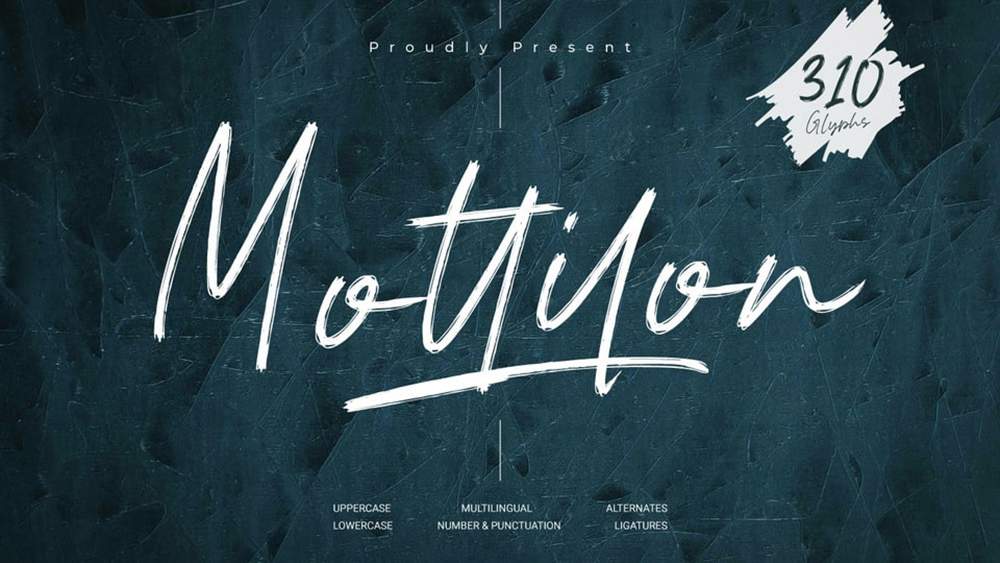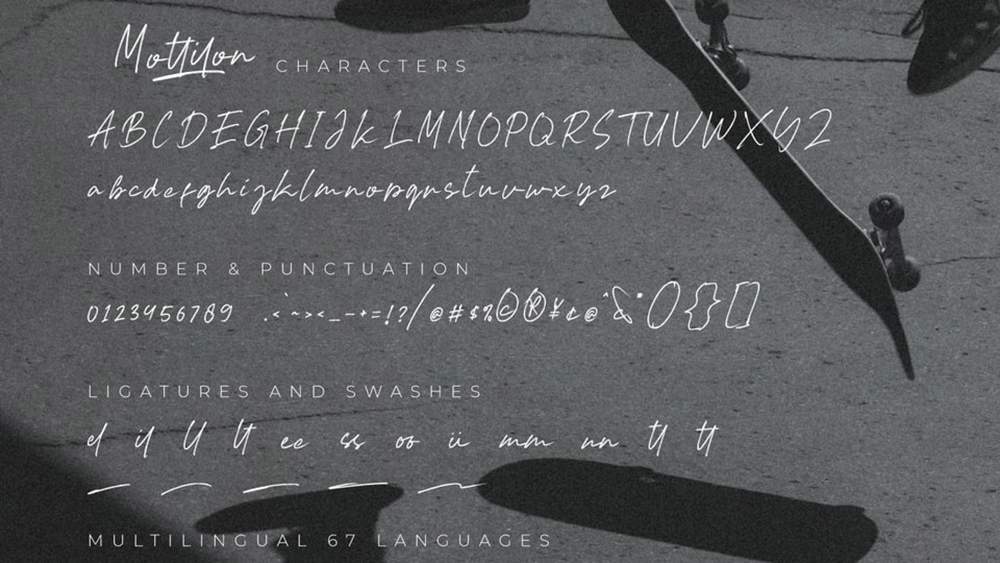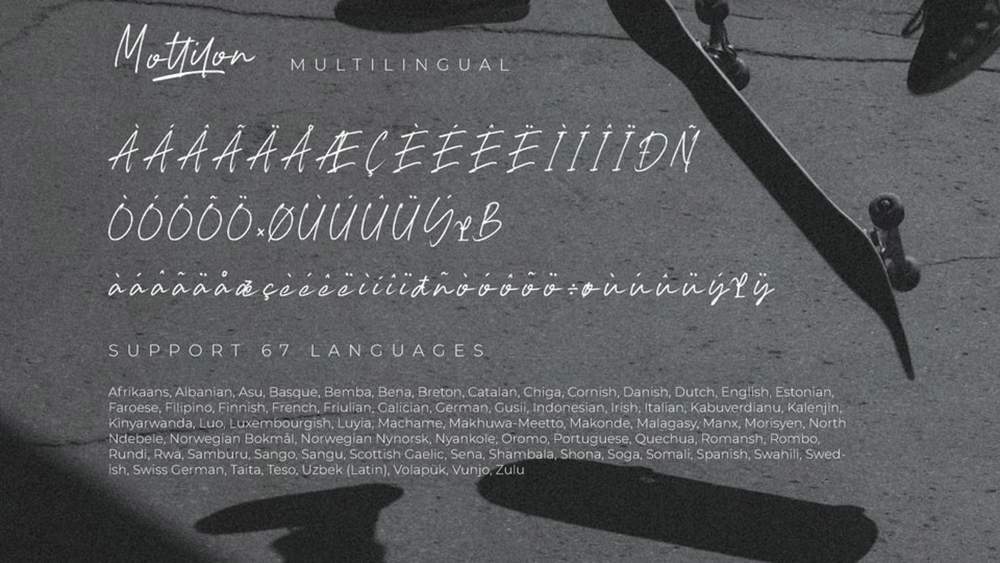
دانلود فونت انگلیسی Mottilon Font
فونت پرمیوم و انگلیسی Mottilon Font یک فونت قلمموی ساده با لیگاتورها و سواشها میباشد که برای برندسازی، لوگو، پوستر، عکاسی و موارد ديگر ایدهآل است.
مزایای استفاده از فونت لاتین Mottilon چیست؟